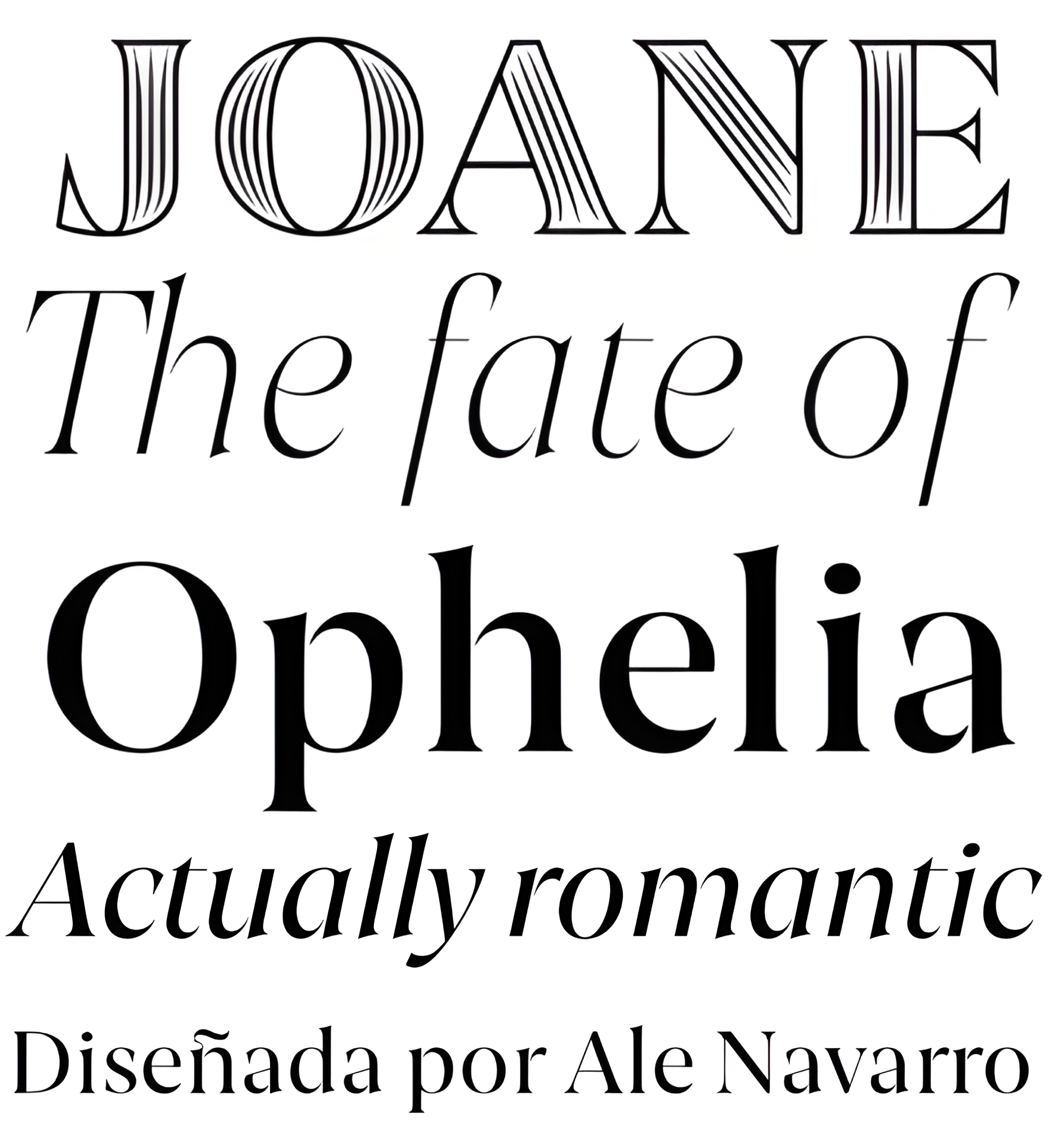
| Descripción | Joane mezcla la elegancia de los didones franceses, las terminaciones caligráficas y las gracias glíficas, por lo que sus rasgos transmiten un cálido estilo único. Además, sus curvas han sido bellamente diseñadas, y también viene en versiones grabada y deco, que añaden más versatilidad a la forma en que puede utilizarse. Joanes es perfecta para revistas, marcas, publicidad, etiquetas, web y envases. Joane es mi primer tipo de letra que se publica en todo el mundo. Para lograr este objetivo, he recibido una ayuda esencial del equipo de W y de mis amigos. Personalmente quiero dar las gracias a Diego Aravena por la paciencia, la buena voluntad y el aprendizaje; por la amistad y el apoyo a Franco Jonas y Raúl Meza. Gracias a su ayuda pude encontrar los tesoros al final del proceso. |